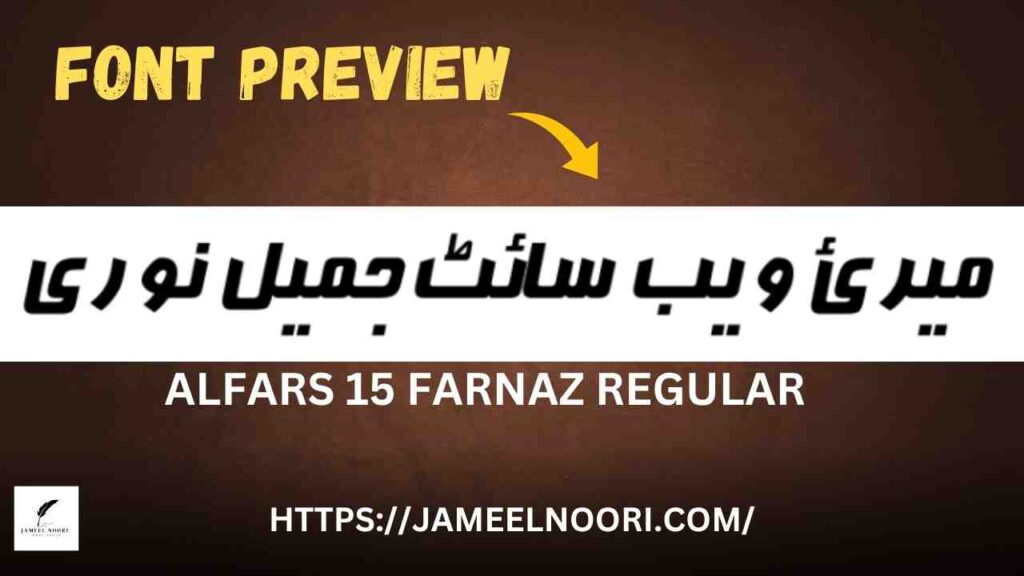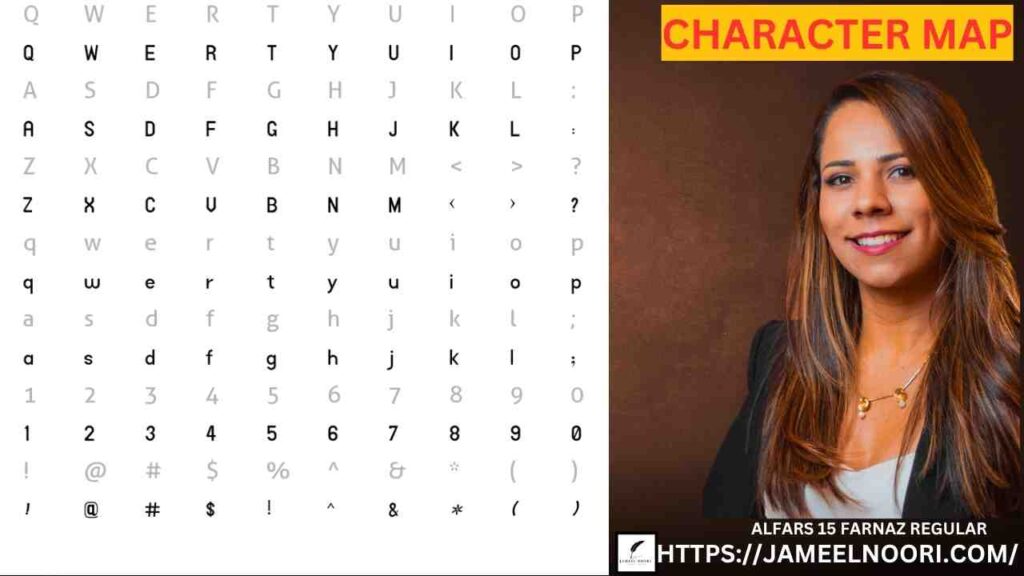
Introduction – Download Urdu Font AlFars Farnaz Regular- Urdu Font Kya Hai?
AlFars Farnaz Font Ke Fawaid
- ✅ Elegant aur balanced Urdu style
- ✅ Perfect for digital Urdu writing and graphics
Kahan Use Kar Sakte Hain AlFars Farnaz Regular Font?
Aap is Urdu font ko istamal kar sakte hain:
- ✅ Urdu blogs aur news articles mein
- ✅ Urdu thumbnails aur social media posters ke design mein
- ✅ Islamic calligraphy aur poetry design mein
Conclusion – Kyun Download Karein AlFars Farnaz Urdu Font?